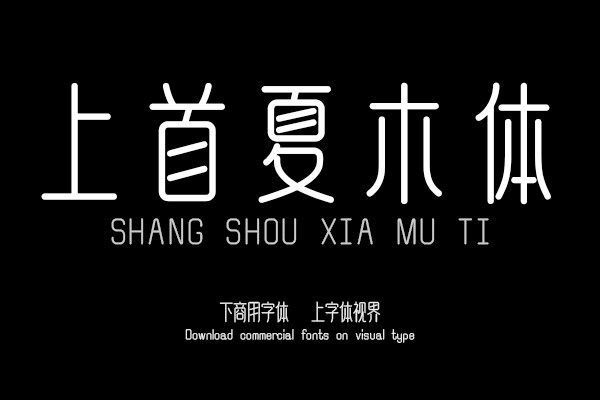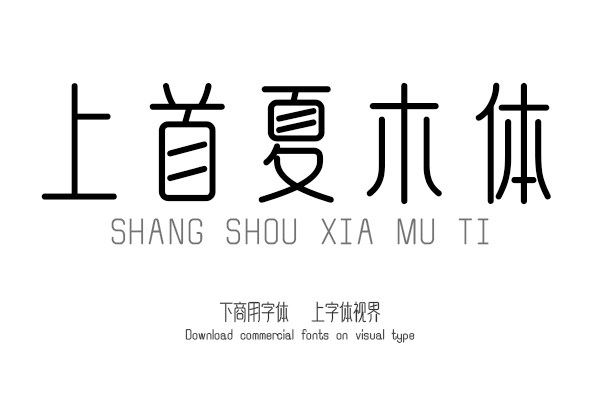
上首夏木体,简体中文约6763字,字体修长,起笔落笔圆角处理,呈现精巧的感觉。适用于搭配标志、广告标语、商业广告等高端属性。购买须知:“下载服务费”与“字体VIP”所获得字体 仅用于个人非商用, 商用请联系付费授权。本字体为电脑用字,手机没有root权限不支持直接手机换字(手机如何root,请自行百度搜索教程)。购买前请先 了解清楚后再付款 ,字体为虚拟产品无法回收 一旦购买不支持退款。